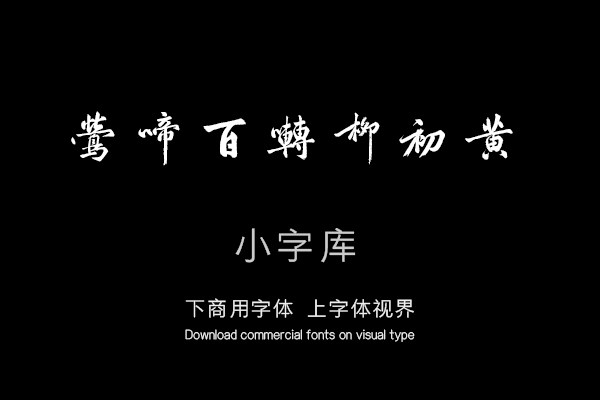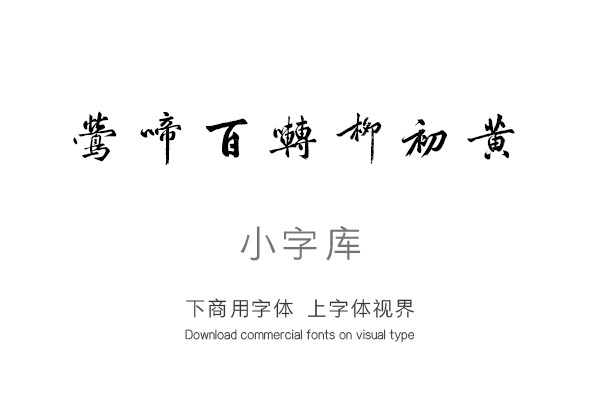
汉标黄庭坚上苑诗帖
《汉标黄庭坚上苑诗帖》是一款根据北宋黄庭坚《上苑诗帖》,经过再次调整制作的小字库,该小字库共收录了该真迹作品中约131个字体。
翠盖龙旂出建章,莺啼百啭柳初黄。昆池冰泮三山近,阿阁花深九陌香。径转虹梁通紫极,庭含玉树隐霓裳。侍臣缓步随銮辂,冈上应看集凤皇。小苑平临太液池,金铺约户锁蟠螭。云中帝座飞华盖,城上钧陈绕翠旗。紫气旋迴双凤阁,青松还有万年枝。从来清跸深严地,开尽碧桃人未知。黄庭坚